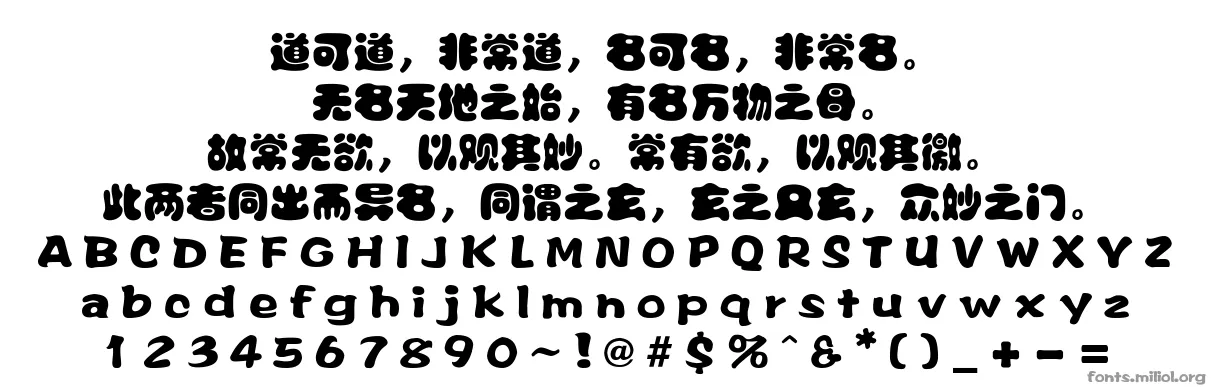
## 方正胖头鱼简体:童趣与个性的完美融合
方正胖头鱼简体是一款极具特色的中文字体,由方正字库设计开发。这款字体以其圆润饱满的笔画和独特的造型风格,在众多字体中脱颖而出。
字体设计灵感来源于儿童涂鸦,笔画末端圆润饱满,犹如胖头鱼般憨态可掬。每个字都经过精心设计,在保持可读性的同时,赋予文字独特的视觉趣味。横竖笔画粗细对比明显,转折处圆滑流畅,整体呈现出活泼可爱的视觉效果。
方正胖头鱼简体特别适合用于儿童读物、卡通漫画、创意设计等领域。其独特的字形能够有效吸引读者注意力,为设计作品增添趣味性和亲和力。在商业应用中,这款字体也能为品牌注入年轻活力,提升品牌辨识度。
这款字体的推出,不仅丰富了中文字体库,更为设计师提供了更多创意选择,展现了中文字体设计的无限可能。